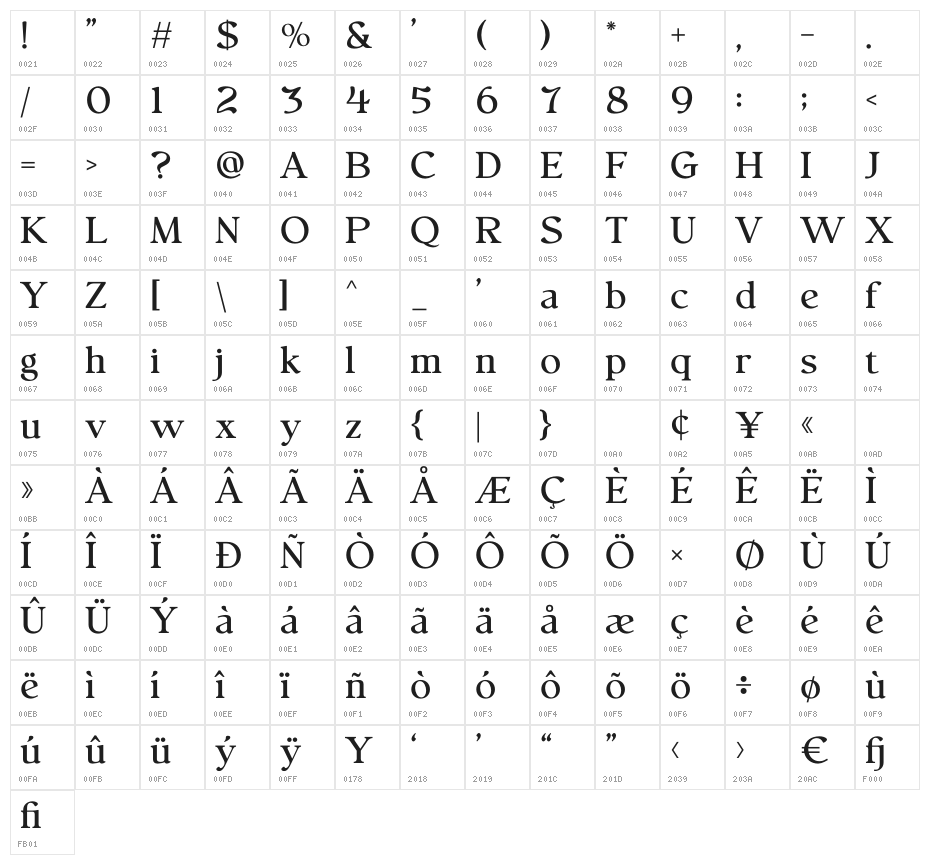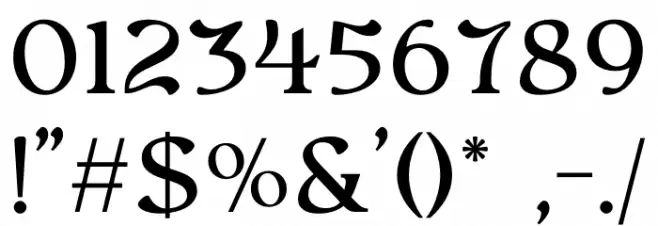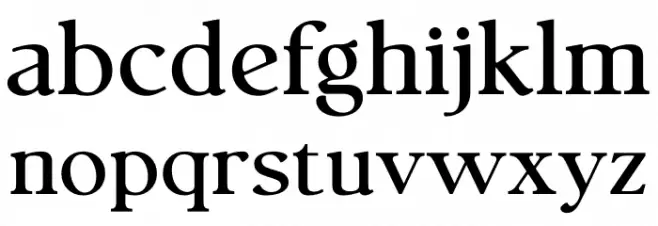
Salfish Font
✎ Serif
| समग्र शैली | Classic |
| उपयोग का मामला | Headlines, Body text, Logos |
| सुझाए गए प्रोजेक्ट | Ideal for book covers, formal invitations, editorial layouts, and branding projects that require a traditional and sophisticated look. |